Ateliers de lettering, créations sur mesure et animations créatives
J’accompagne entreprises, collectivités, bibliothèques et particuliers dans des expériences créatives autour des mots, du geste et de la beauté du fait-main.
Je propose des ateliers individuels ou collectifs : fresques participatives, vitrines, affiches, cartes, objets personnalisés…
Chaque projet est pensé pour être accessible, esthétique et porteur de sens, même pour des débutants.
Ateliers Team Building
Atelier fresque ou affiche collaborative
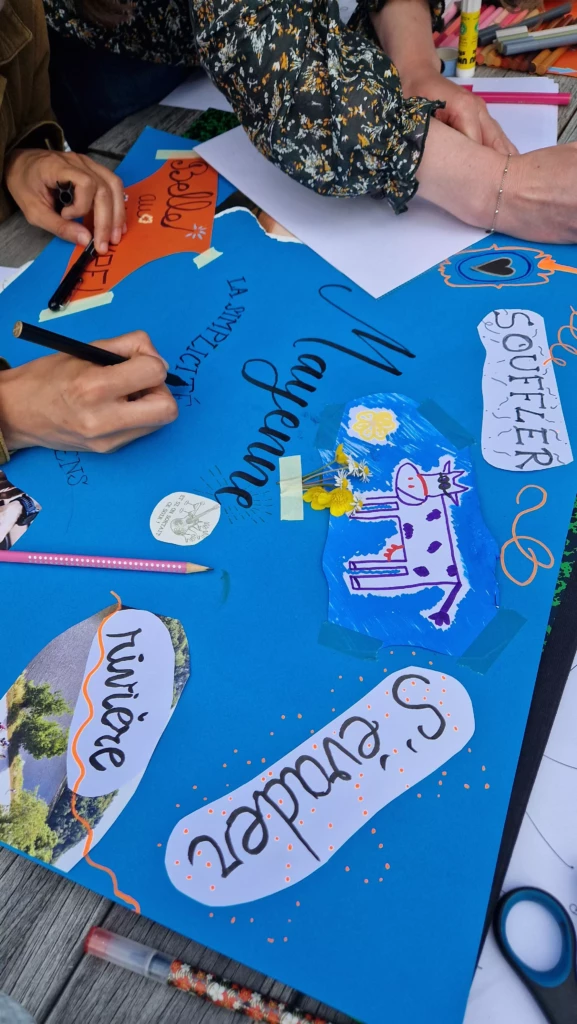
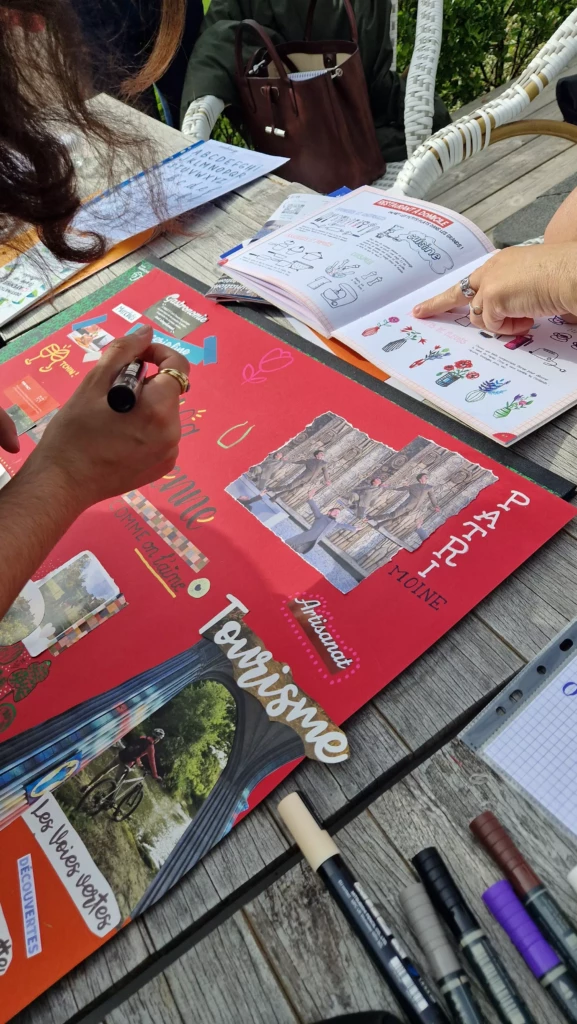
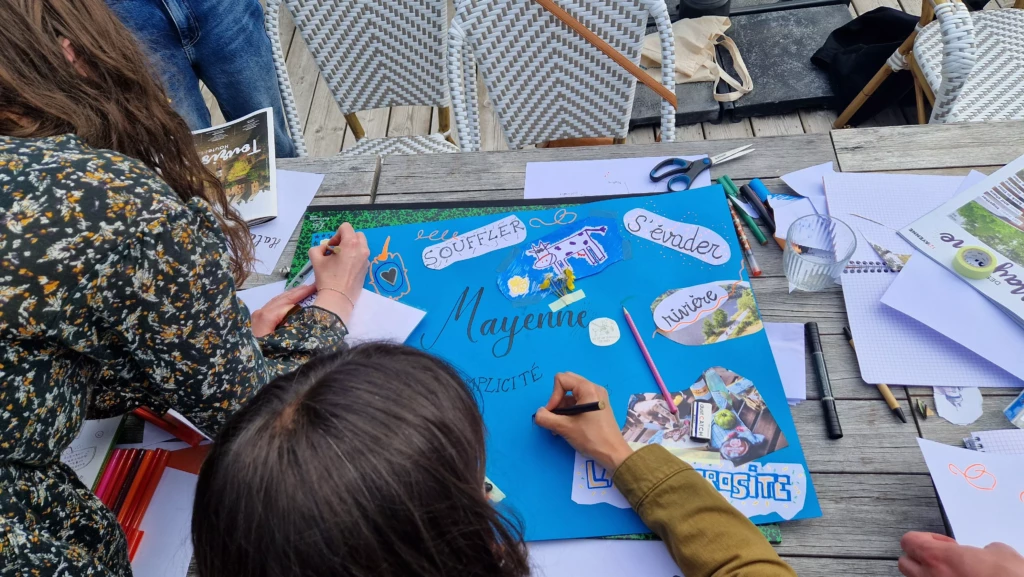
Marque-pages participatifs
Chaque personne écrit un mot ou un dessin et les marque-pages tournent jusqu’à ce que chacun ait écrit. Ainsi tout le monde repart avec un souvenir personnalisé de l’événement
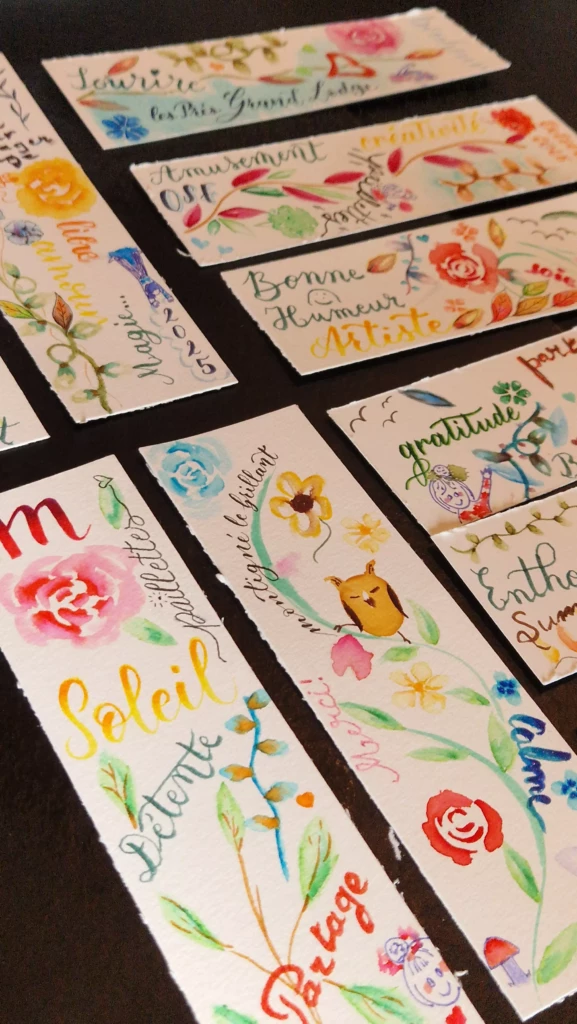
Travaux personnels
Quelques exemples de mes derniers travaux. J’ai une prédilection pour le « brush lettering » et les encres aquarelle. Je privilégie le fait-main et le travail manuel (plutôt que digital). En revanche, j’aime tous les supports, du papier à la fresque murale en passant par les vitrines ou les tableaux noirs !!!